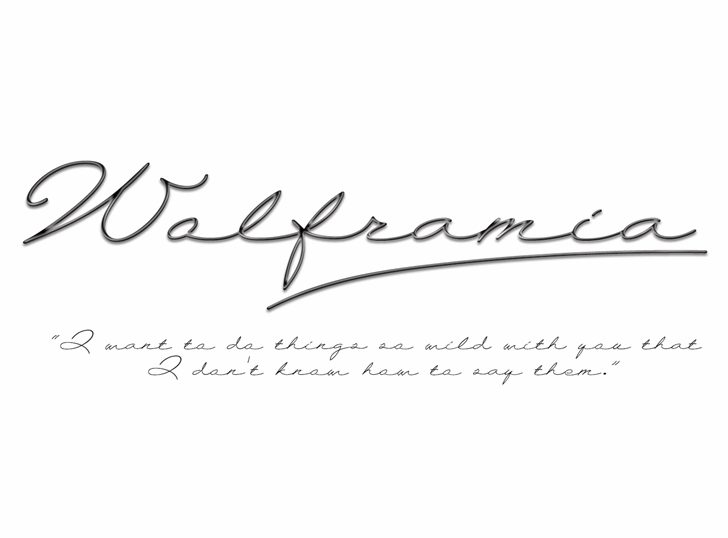
Wolframia é uma fonte moderna com aparência de grafite, desenhada para criar visuais chamativos. Ela se assemelha a escritas manuscritas e casual, tornando-a perfeita para headlines, convites, felicitações ou anúncios elegantes. Wolframia é uma extensão da fonte Latin Extended-A e usa funções OpenType, incluindo o símbolo Bitcoin. Este design foi dedicado ao cientista Wolframio, popularmente conhecido como Tungsten na América do Norte. A fonte oferece várias chaves para ornamentação, que vão desde os parênteses até as barras de corchete. Esta fonte é perfeita tanto para designers quanto para marqueteiros buscando um visual único e moderno. Se você está procurando uma fonte criativa com uma aparência chamativa e versátil, Wolframia pode ser a escolha perfeita.